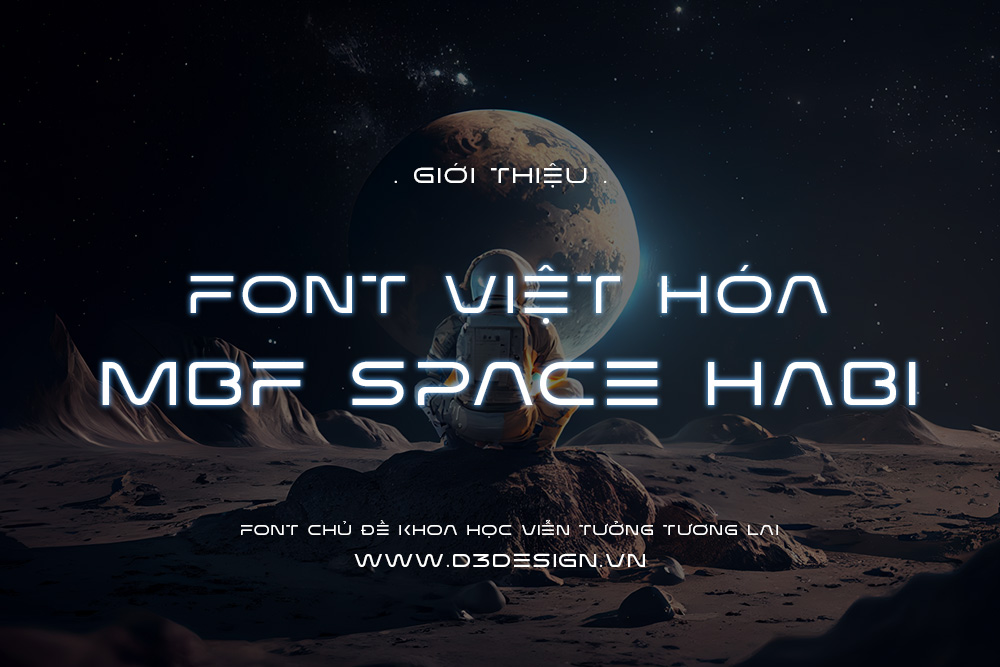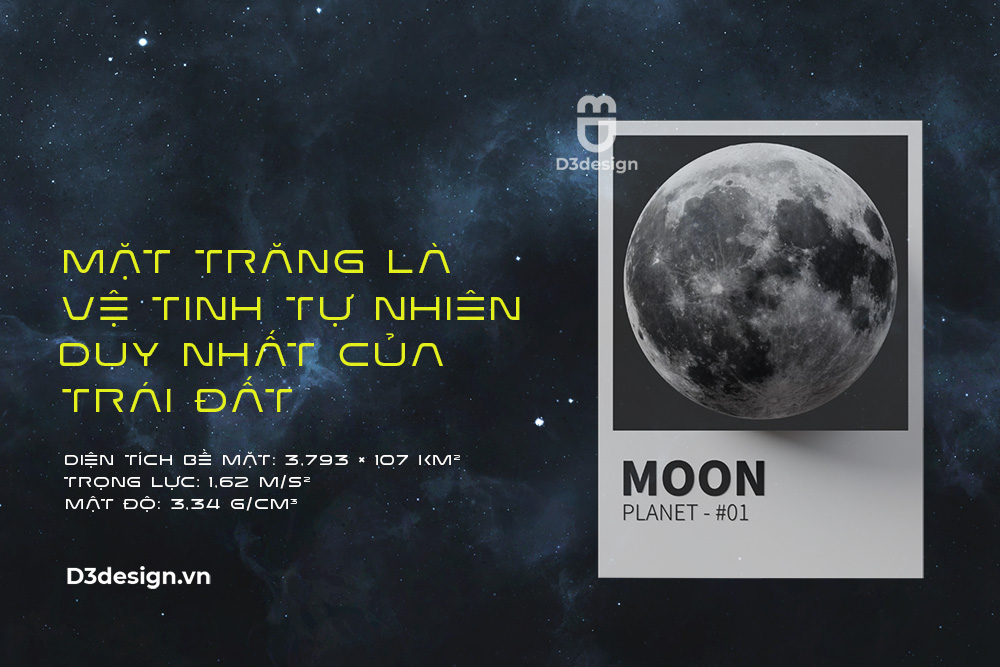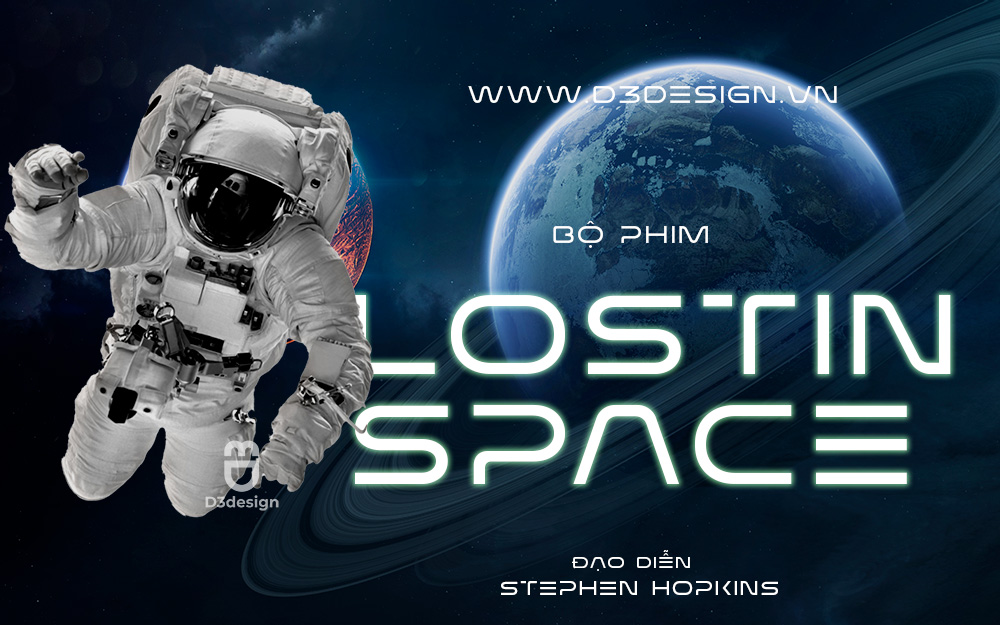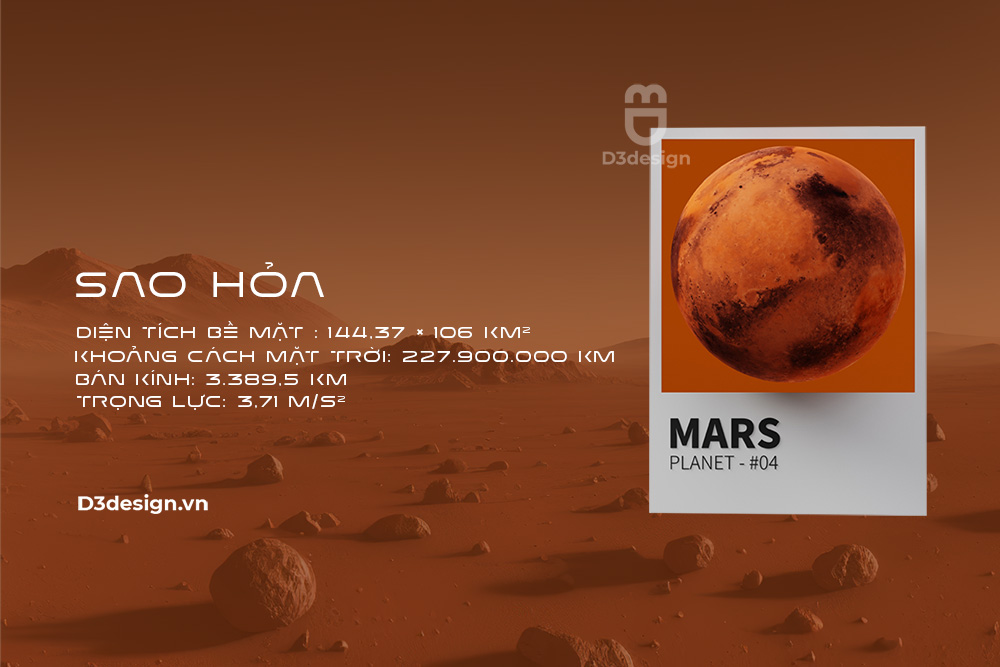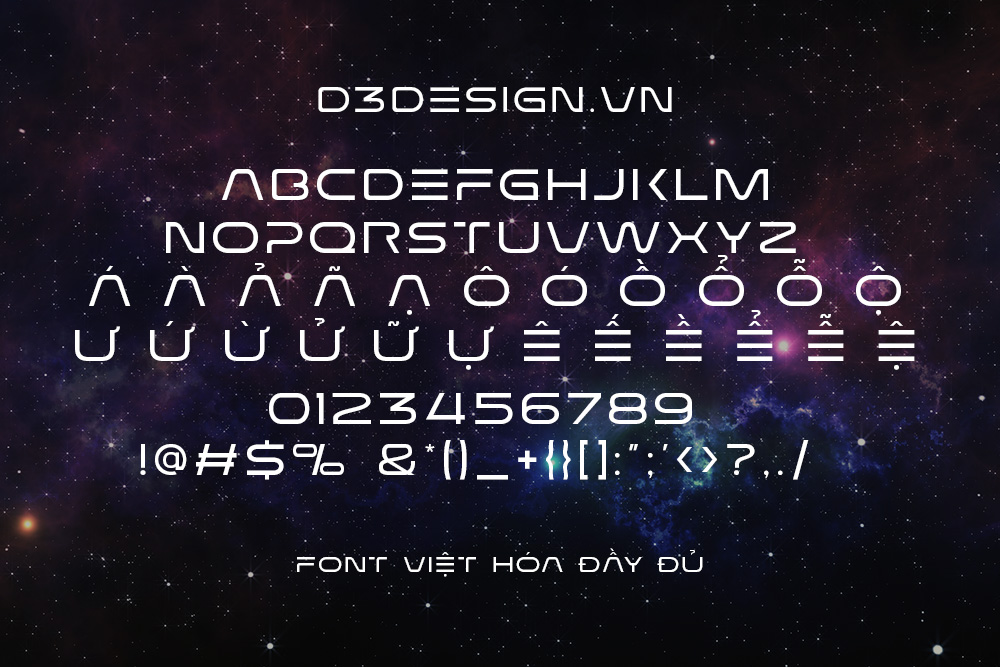
Font Việt Hóa - MBF Space Habitat Mang Phong Cách Khoa Học Viễn Tưởng Tương Lai
MBF Space Habitat font được lấy cảm hứng từ không gian nơi những bí ẩn khi mà các nhà khoa học vẫn chưa tìm ra được cách lý giải hợp lý cho những bí ẩn không gian này. Các nét chữ bo tròn và cạnh sắc nét, nhấn mạnh chủ đề khoa học viễn tưởng tương lai (futuristic).
Nếu bạn vẫn đang tìm một futuristic font tuyệt vời và hoàn toàn miễn phí cho bạn sử dụng ngay vào thiết kế của mình thì hãy thử MBF Space Habitat nhé. Font hoàn hảo cho các thiết kế như logo, tiêu đề, thiết kế áo phông, quotes...